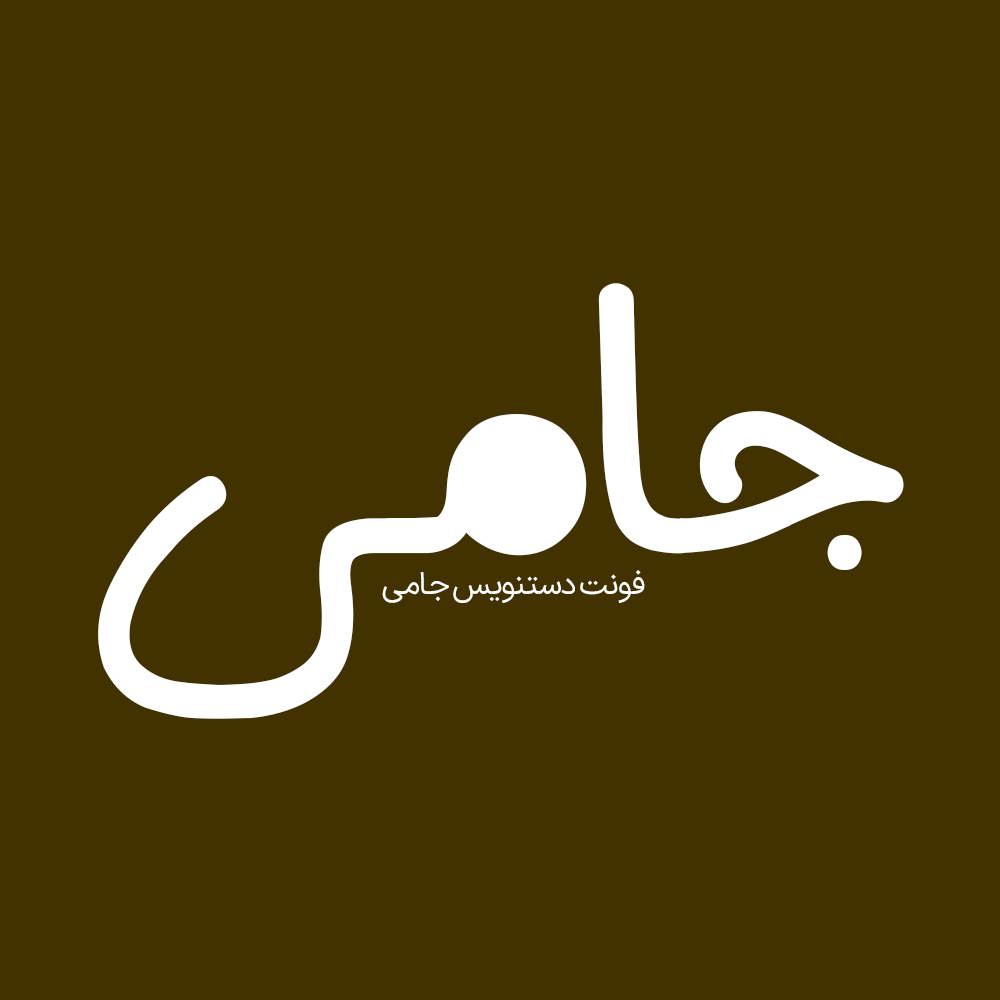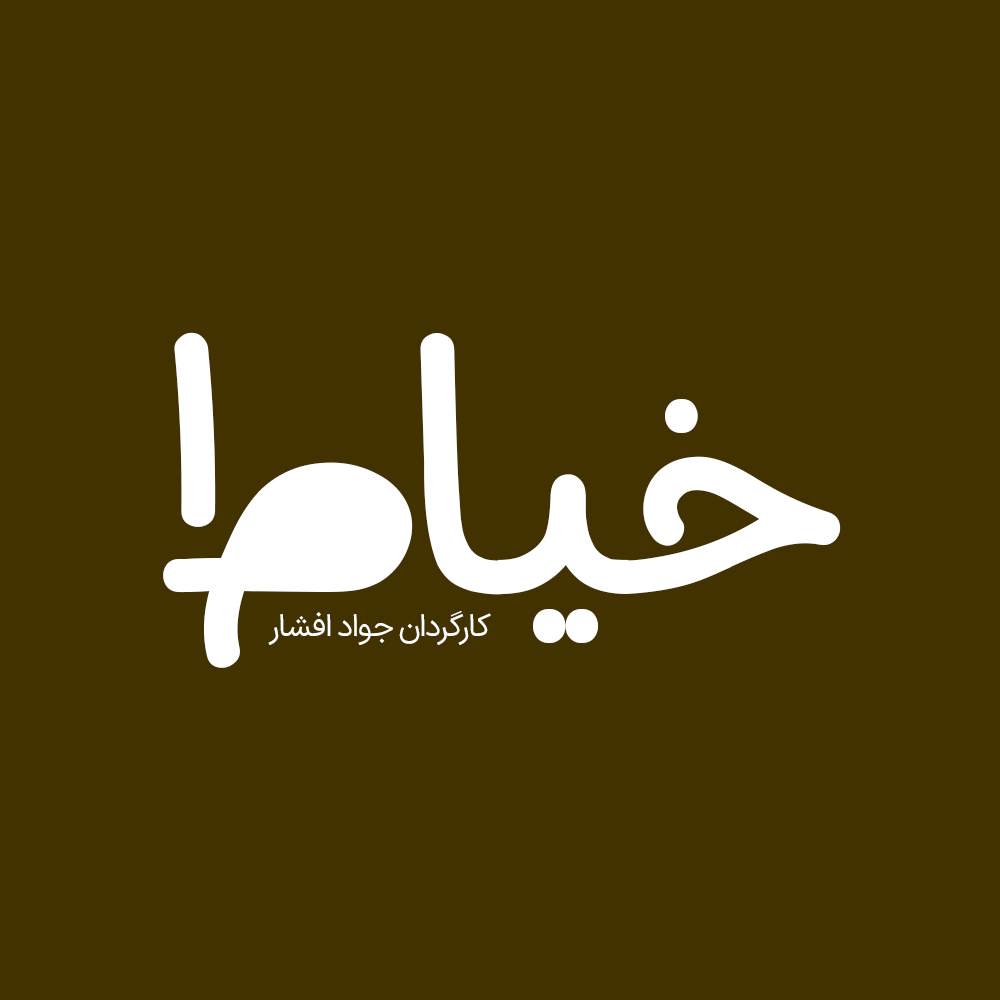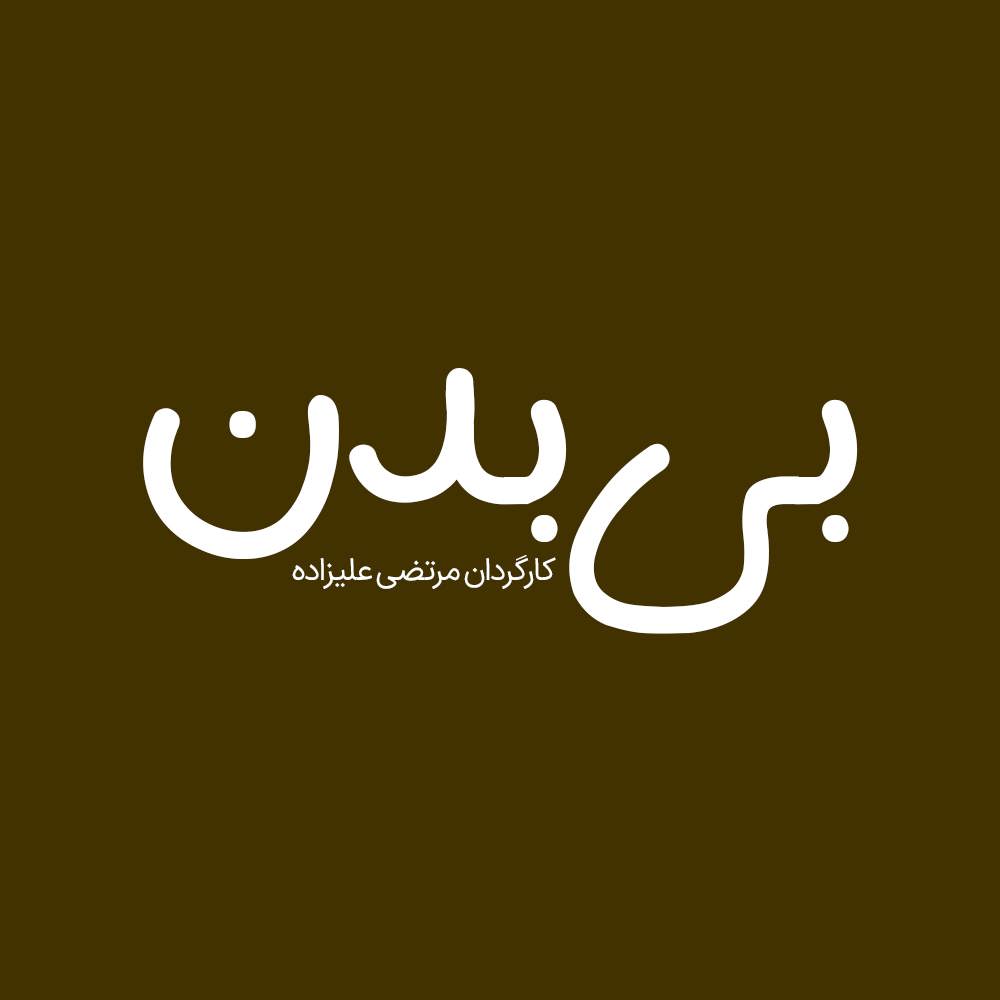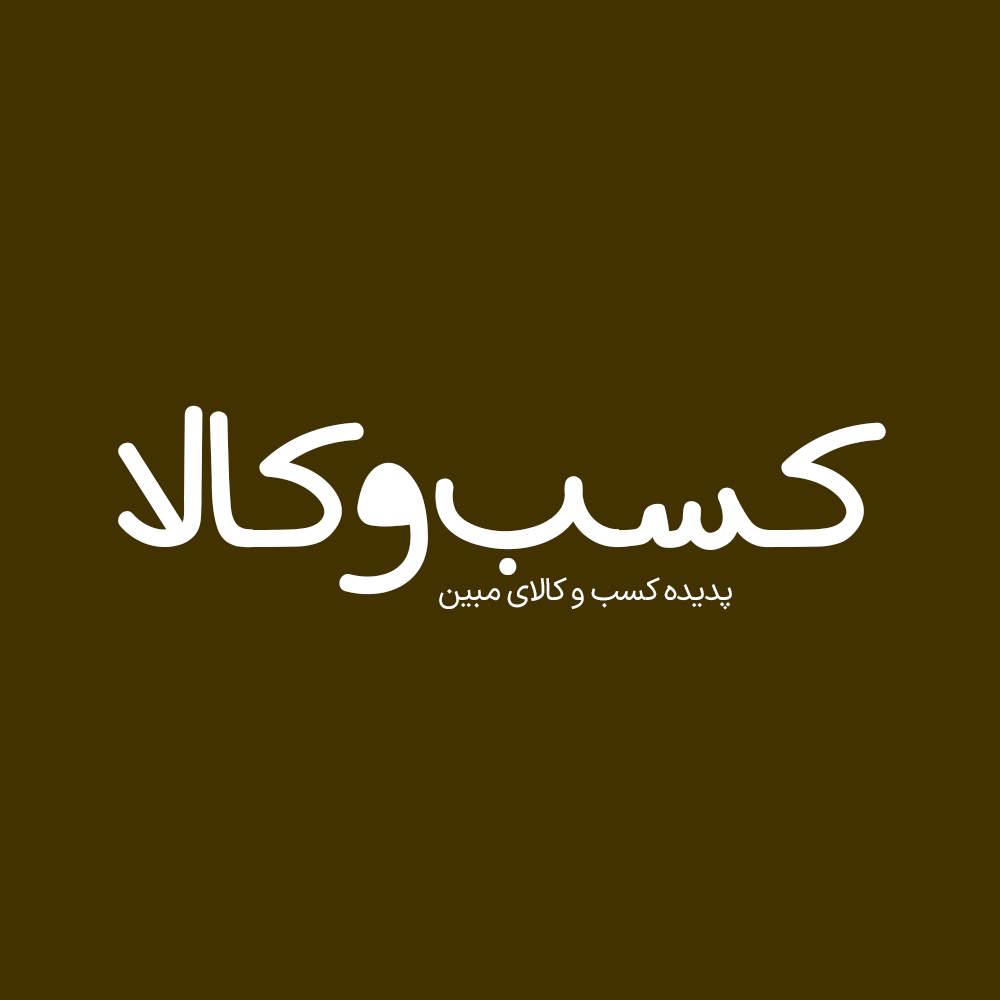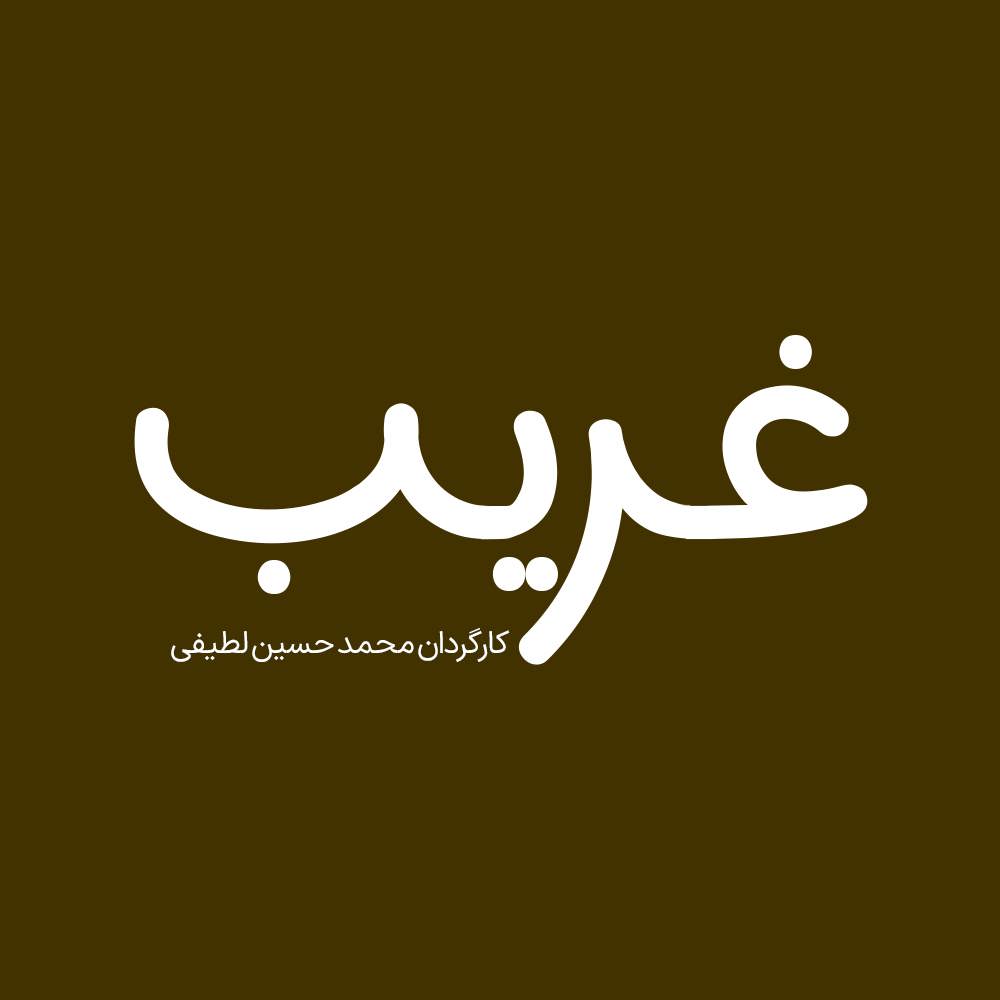
فونت فارسی جامی Jaami Font
فونت دستنویس جامی یک فونت بسیار زیبا و حرفه ای و متفاوت برای طراحی انواع امور گرافیکی به خصوص طراحی انواع لوگوتایپ و تایپوگرافی می باشد…
فونت دستنویس جامی یک فونت بسیار زیبا و حرفه ای و متفاوت برای طراحی انواع امور گرافیکی به خصوص طراحی انواع لوگوتایپ و تایپوگرافی می باشد شما با استفاده از فونت جامی میتوانید لوگوتایپ و طراحی های زیبایی خلق کنید.
فونت جامی یک فونت عربی، فارسی سازی و بهینه شده است که برای طراحی انواع امور گرافیکی به خصوص طراحی انواع لوگوتایپ و تایپوگرافی می باشد. از آنجایی که فونت هایی عربی فاقد حروف “گچ پژ” هستند و مشکلاتی در تایپ حروف “ک” و “ی” دارند در فونت جامی حروف “گچ پژ” و همچنین اعداد فارسی و حروف انگلیسی اضافه شده است و حروف ( آ ـآ، إ ـإ، أ ـأ، ئ ـئ، ـب، ـپ، ـت، ـث، ـد، ـذ، ط ـط، ظ ـظ، ق ـق، کـ ـکـ ـک ک، گـ ـگـ ـگ گ، ی ـی، ـلا بازطراحی شده اند تا بتوانید تمامی متن فارسی را به وسیله این فونت تایپ کنید. در ادامه برای شما نمونه تایپ های این محصول حرفه ای رو آماده کردیم که میتونید مشاهده کنید.
• مناسب طراحی بسته بندی ها و چاپ
• فونت ویژه تبلیغات محیطی
• فونت طراحی کاور اینستاگرام
• فونت حرفه ای برای تولید محتوا
• فونت فارسی طراحی وبسایت
• فونت طراحی لوگو تایپ فارسی
• مناسب استفاده در تابلو های چلنیوم و طراحی حروف
پیشنمایش و نمونه تایپ های فونت جامی